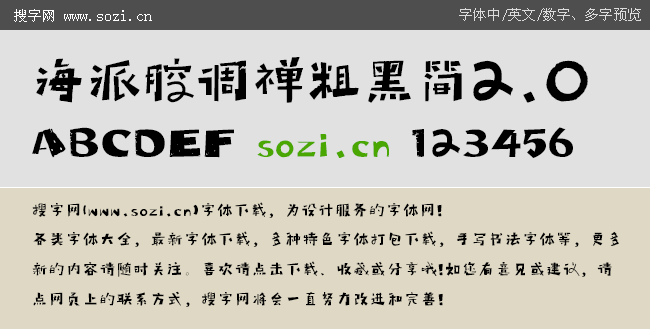
海派腔調(diào)禪粗黑簡2.0
搜字網(wǎng)提供一款海派腔調(diào)禪粗黑簡2.0中文字體下載,海派腔調(diào)禪粗黑簡字體是一款左粗右細、整體效果非常出眾的簡體中文字體,適合應(yīng)用于廣告設(shè)計、名片設(shè)計、包裝印刷、產(chǎn)品設(shè)計等應(yīng)用。
• 風格類別: 海報POP體